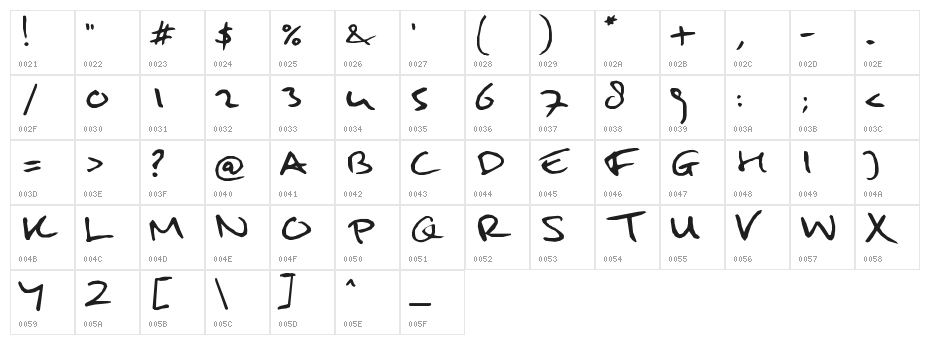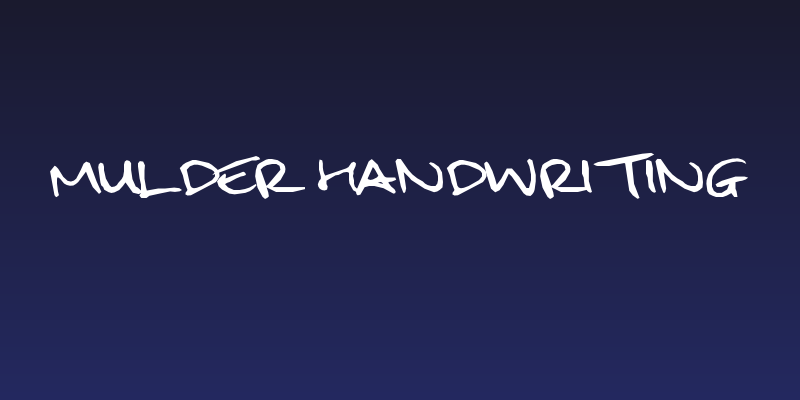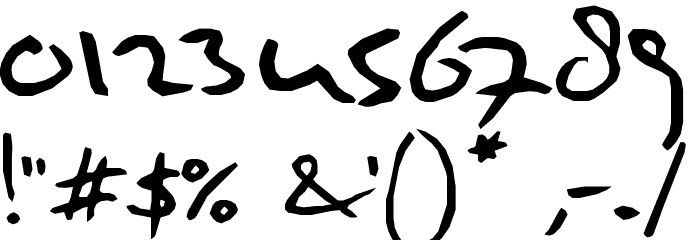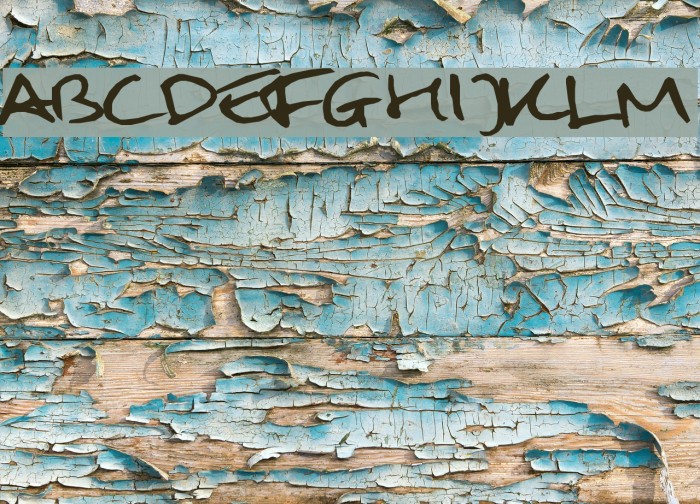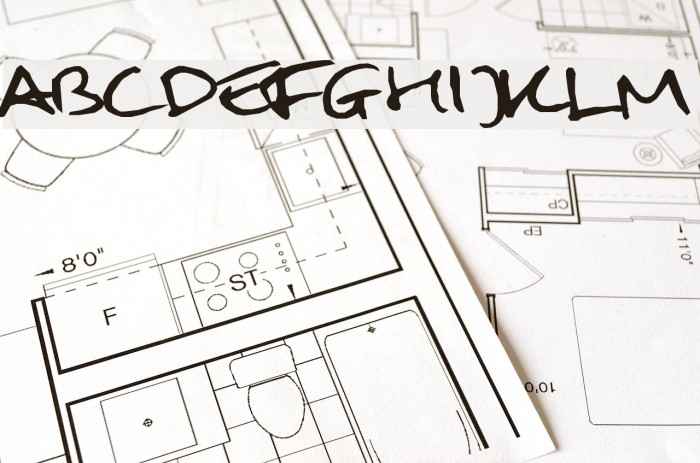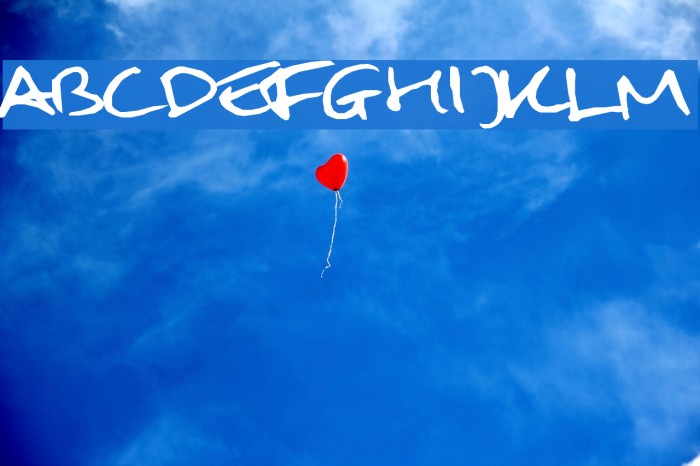
Mulder handwriting Font
| Estilo geral | Casual, Organic |
| Caso de uso | Headlines, Informal text, Creative projects |
| Projetos propostos | Ideal for personal invitations, greeting cards, creative branding, and informal communication. |